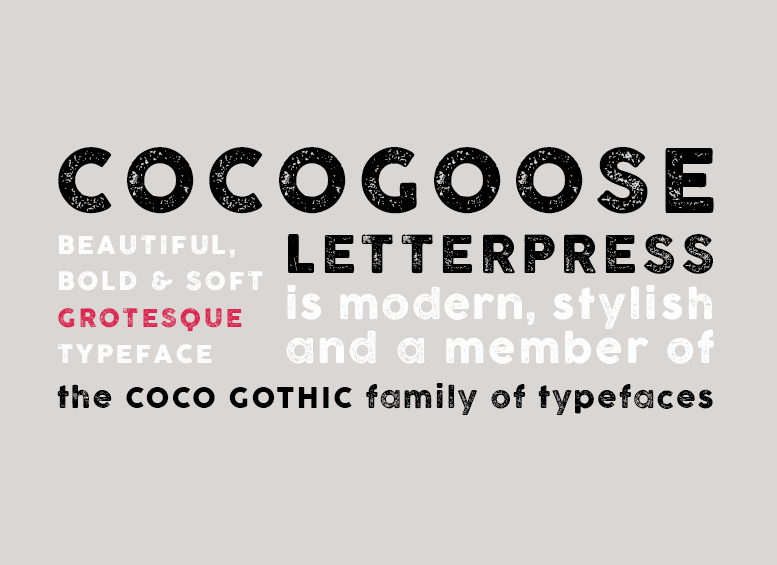
A fonte ‘Cocogoose Letterpress’ é uma versão de nossa popular fonte ‘CocoGoose Typeface’. Esse estilo traz à tona a essência do manuseio manual, criando um look que remonta ao mundo da impressão em letras pombas. Utilizando substituições de tipo aberto para selecionar aleatoriamente cada letra entre quatro variações diferentes, resulta num visual verdadeiramente inspirado na tecnologia tradicional do letreiro de pressão sem os aspectos digitais que frequentemente causam um efeito repetitivo ou antigo. Para quem está buscando uma fonte com o estilo moderno da digital, mas deseja um toque nostálgico e autêntico, a Cocogoose Letterpress é uma escolha interessante para seus projetos de design. Esta fonte perfeita para aplicar em materiais impressos tradicionais ou manufaturados a leitura.